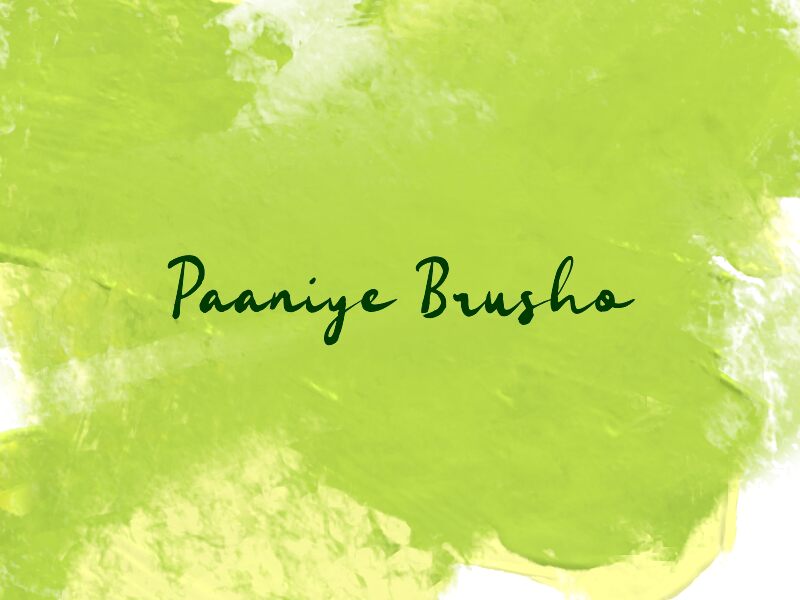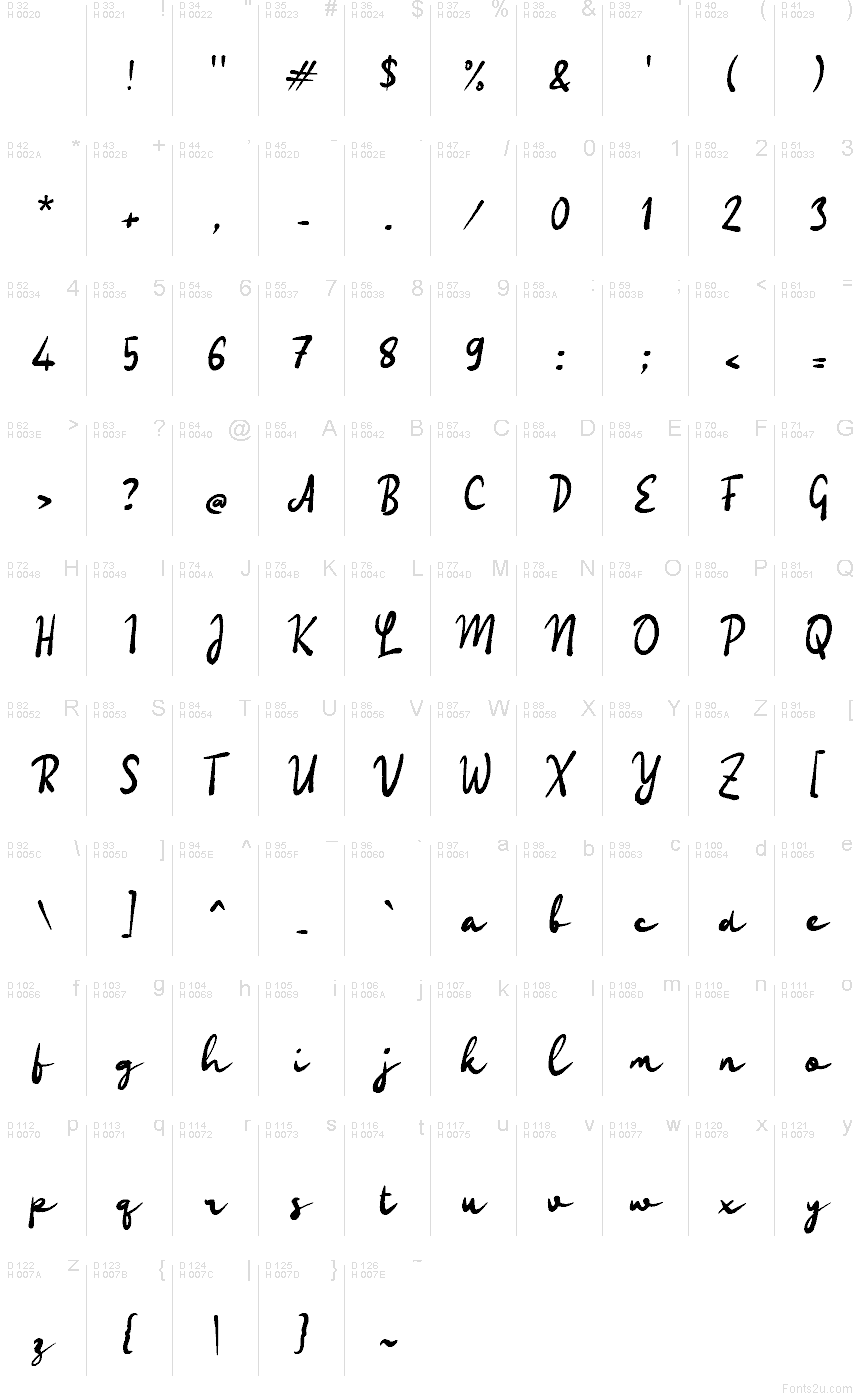
Paaniye Brusho
Paaniye Brusho od Wep je bezplatné písmo typu brush script s rychlým, nakloněným rytmem, který působí, jako by byl napsán jedním sebejistým tahem. Písmena střídají vysoké, rozmáchlé tvary s nižšími zaoblenými tahy, což dává řádku ležérní rukopisný dojem namísto strojené kaligrafie.
Díky této přirozené lehkosti je ideální volbou pro vývěsní štíty kaváren, etikety produktů, citáty na sociální sítě, neformální obaly nebo přáníčka. Zejména krátké nadpisy a nápisová loga těží z jeho svižného, plynulého vzoru, který dodává slovům pohyb a osobní nádech, aniž by působil příliš dekorativně.